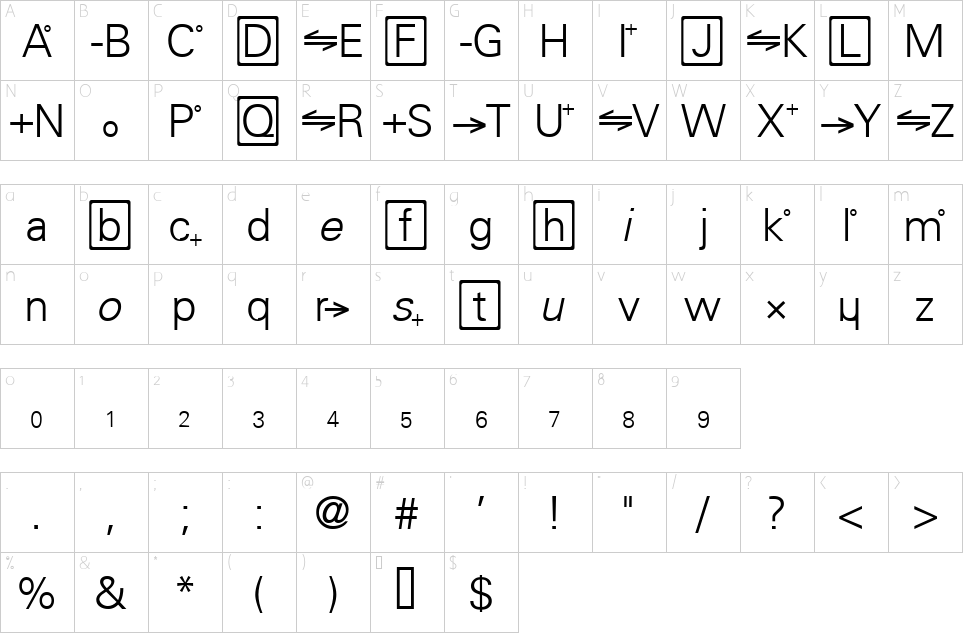
A fonte Chemistry, disponível gratuitamente tanto para Windows quanto para Mac, foi criada por No Images Fonts e tem sido baixada mais de 6.744 vezes. Este fonte, dedicado à ciência e à química, oferece uma aparência atraente e versátil para textos técnicos, resumos de reações químicas ou mesmo nomes químicos. Suas linhas precisas e a simetria de suas letras podem ajudar a destacar o conteúdo científico em seus projetos. Com seu design cuidadosamente pensado, Chemistry é uma excelente opção para quem busca uma fonte moderna para usar em documentos acadêmicos ou relatórios científicos.